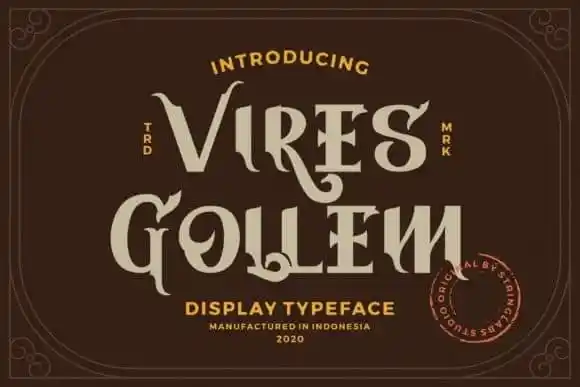
Vires Gollem Display Font – Download Grátis
A Vires Gollem Display Font é uma escolha perfeita para projetistas digitais buscando uma mistura arrojada de elegância moderna e roupas vintage, criada pela StringLabs. Suave e balanceado, ela oferece curvas que se encaixam na medida certa, fornecendo um visual sofisticado e bem equilibrado. Esta fonte, única e audaz, é perfeita para aqueles que buscam uma nova inspiração em sua versatilidade de estilo. Seu amplo leque de alternativas estilizadas oferece várias opções criativas e são ideais para headlines, logotipos, cartazes, embalagens, camisetas, postais e muito mais. O Vires Gollem Display Font é uma escolha ótima para quem busca um toque único em seus projetos visuais.